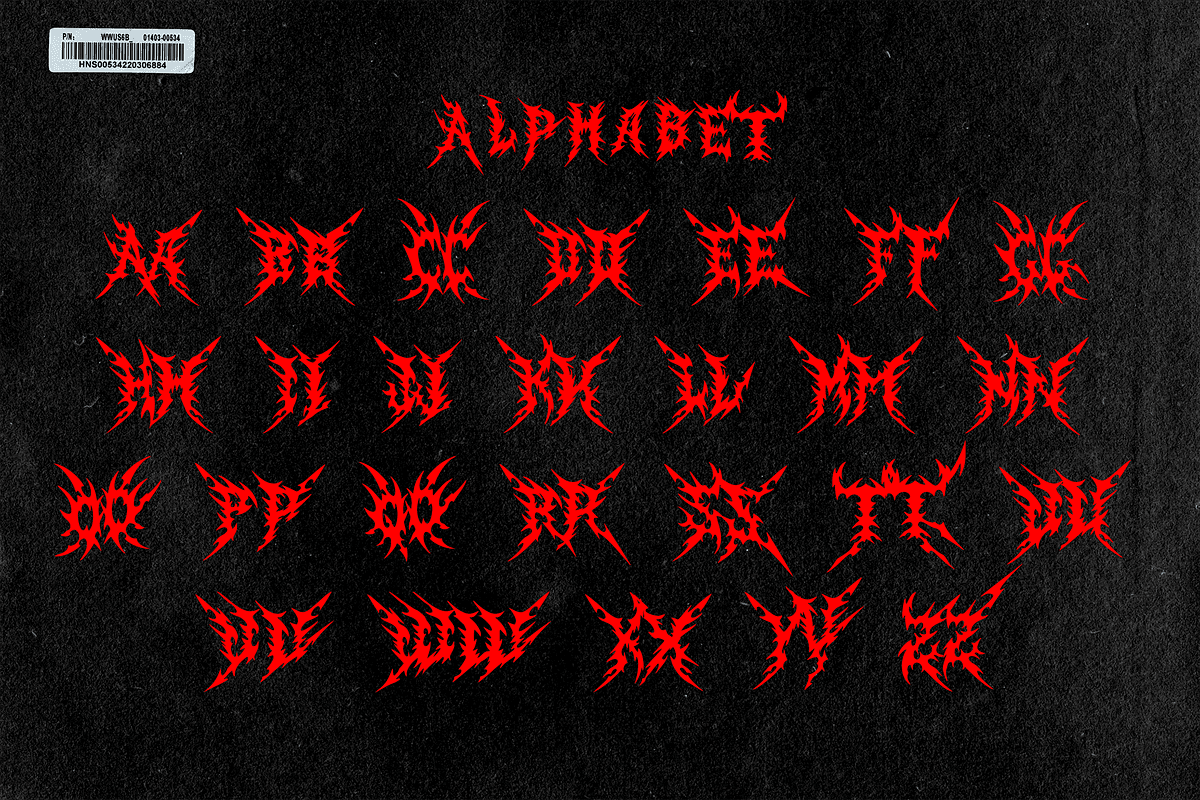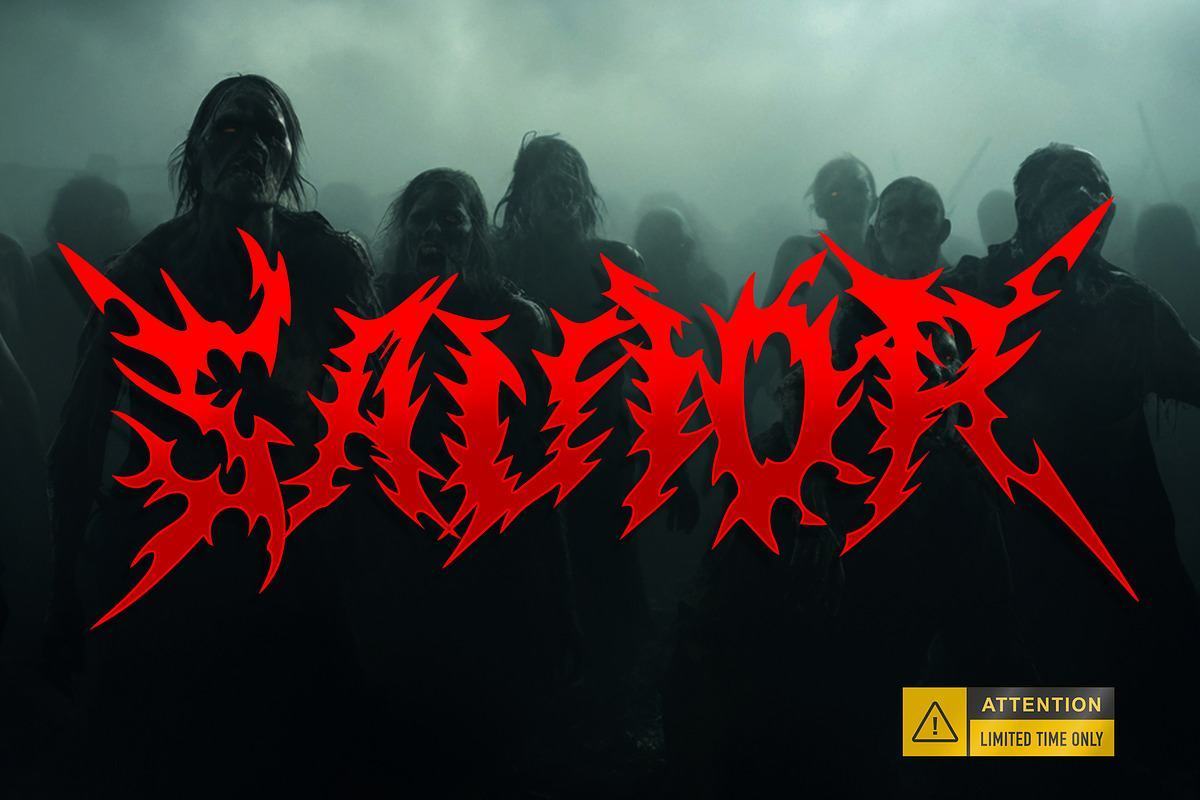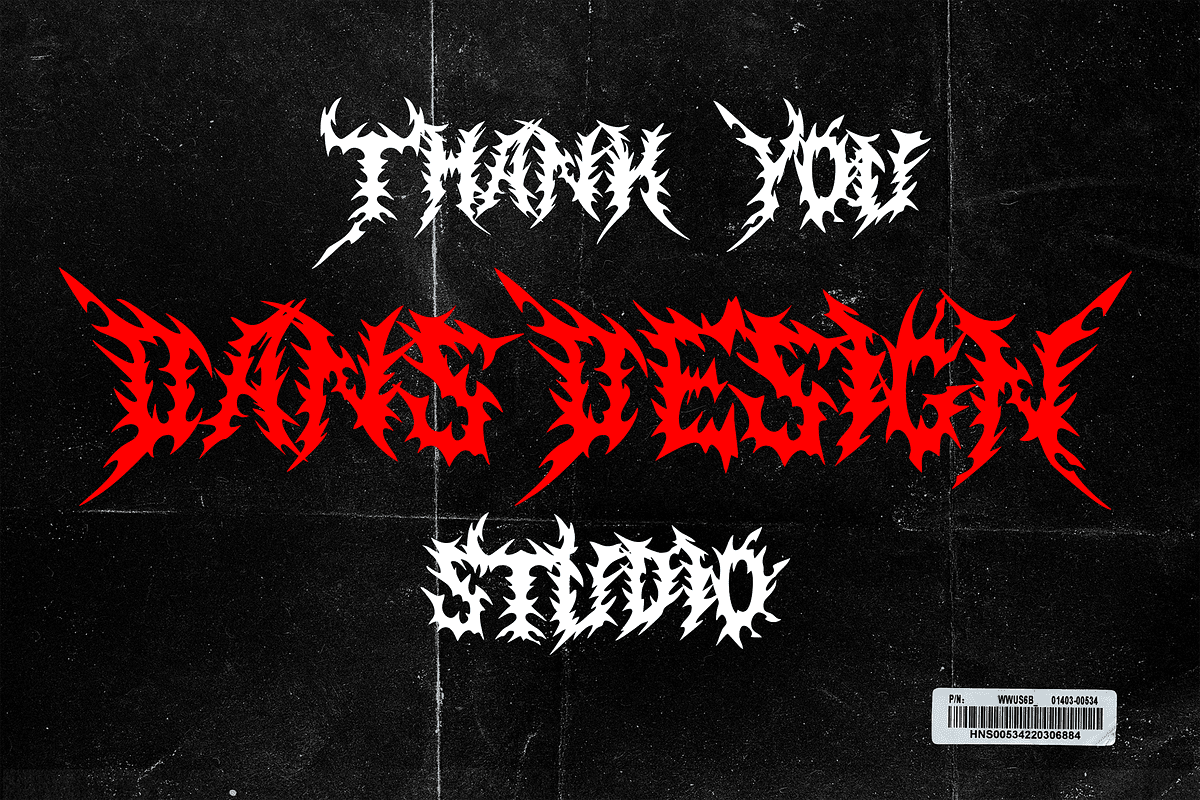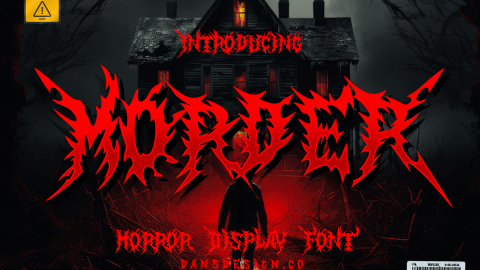
Phông chữ kinh dị kim loại MorderR
Phông chữ MordeR Metal Horror Font là phông chữ Blackletter khác biệt, có độ chi tiết cao và sang trọng. Nó sẽ là sự lựa chọn tuyệt vời cho các thiết kế đô thị cổ điển tinh tế, thương hiệu kinh doanh hình xăm, logo, thiết kế cổ điển, phim, áp phích, trang phục, hình minh họa, v.v.